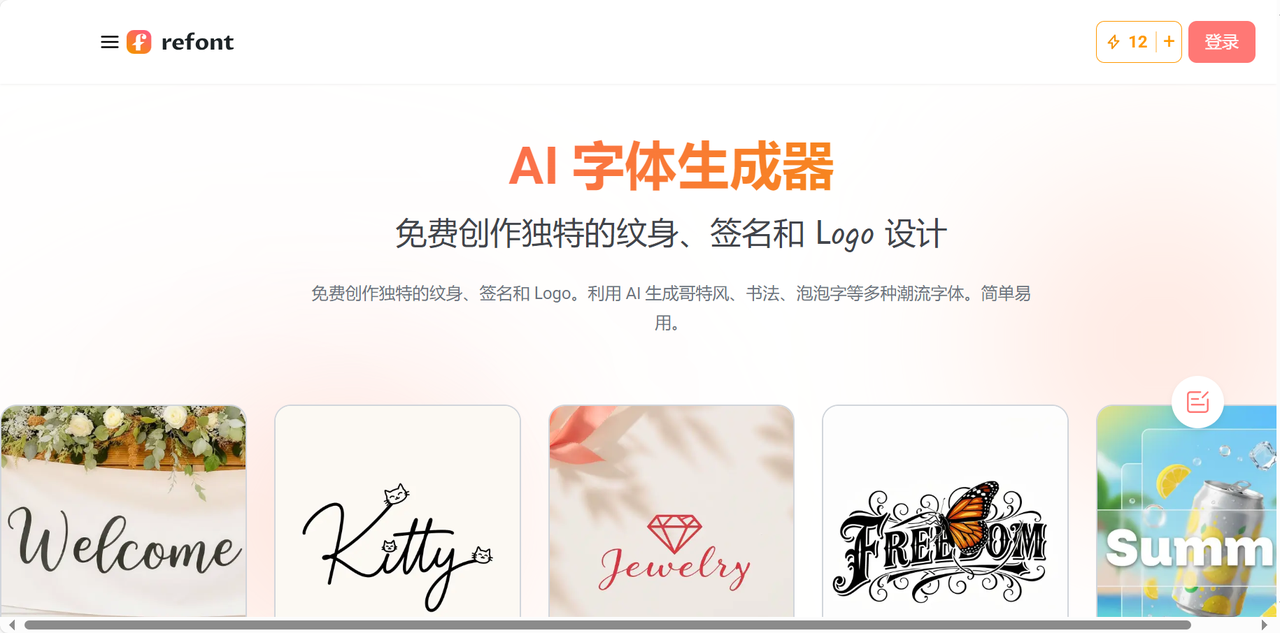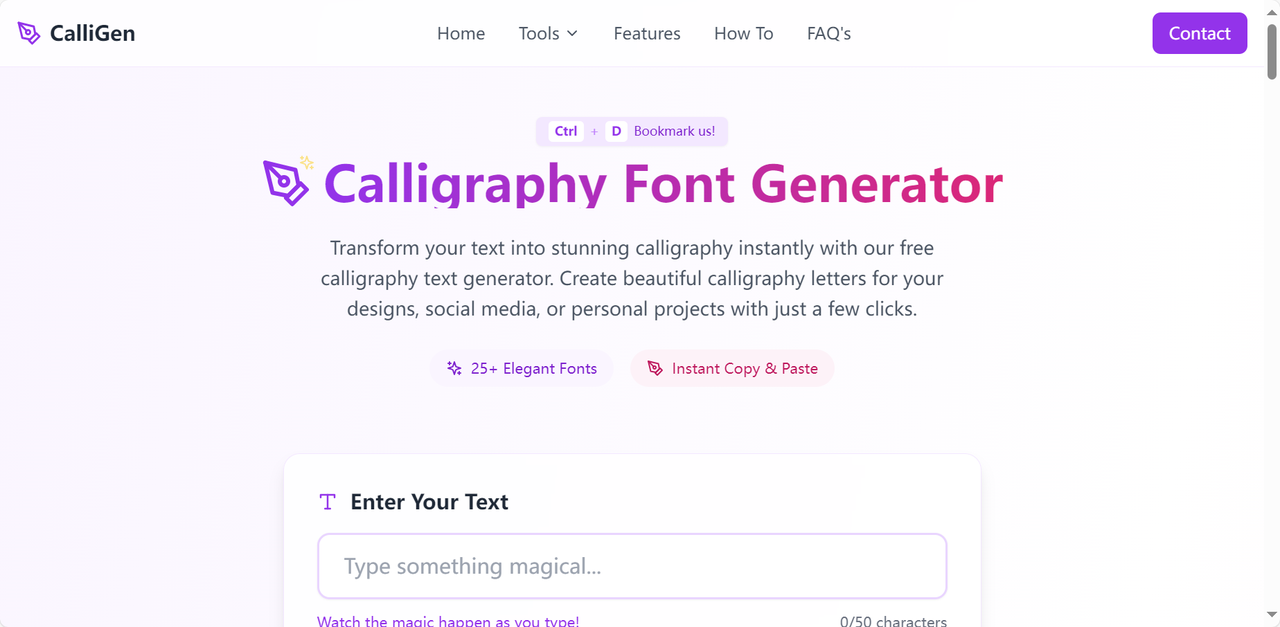
告别手写!在线毛笔字生成工具,透明背景直接下载
没学过书法可以拥有好看的毛笔字字体吗?答案当然是可以!毛笔字不同于日常设计中的其他字体,核心特点在于笔画的粗细变化、飞白墨韵、起收笔锋及手写感,兼具文化意蕴和视觉表现力。而设计作品里经常会用到的毛笔字体正是融合了古代书法的结构特点以及现代数字化设计的简约易读。在线毛笔字生成工具的运行逻辑就是选好字体风格,直接输入你想要的文字,就可以在线获得同款毛笔字,透明背景图片直接下载,拖进任何设计软件里都能用。今天这篇文章,带你认识 4 款实用性极高的在线毛笔字生成工具,一起来看看吧。
一、字由
字由是国内规模领先的字体管理工具,它不仅拥有超多有品质保障的字体资源,还有免费实用的 AI 工具,大大提升你的设计效率。在线生成毛笔字正是需要用到字由的 AI 字体功能,不需要自己写提示词,也不需要懂 AI 模型参数,选择模板、输入文字、一键生成三步搞定毛笔字体。用户只需要在字由官网内找到 AI 字体的页面,可以按照风格进行毛笔字筛选,然后点击“做同款”,就可以一键生成图片同款毛笔字,最好自定义文字的字数和样图内一致,这样生成效果更准确逼真。
我用字由生成毛笔字还是比较频繁的,目前来看它生成的字体结果与默认效果图高度一致,还没有出现过偏差,笔画保留了自然手写感,也不会有文字错位或者变形的问题。而且生成的毛笔字体支持导出透明背景的 PNG 图片,直接拖入 PS 等设计软件即可使用,不用抠图、不用去底,非常方便!
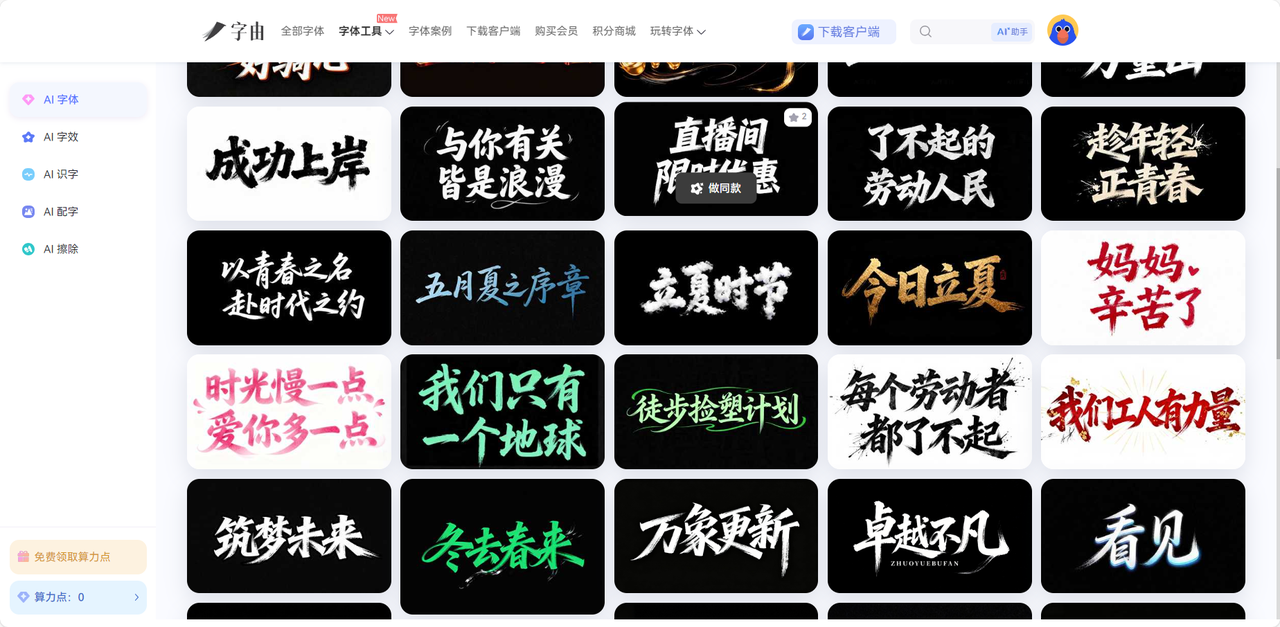
二、Refont AI
Refont AI 是一款以 AI 驱动的书法毛笔字生成工具,支持中文和英文,覆盖草书、隶书、行书等多种字体风格。这款工具最大的亮点是书法风格的 AI 渲染功能,比如选择草书风格,系统会自动模拟草书的笔锋及字形;选择隶书风格则会精准还原“蚕头燕尾”的壁画特征,保证你的字体完全符合书法效果。Refont AI 还内置了名家风格选项,也就是说用它可以模仿一些著名书法家的笔触风格,对于一些书法字体要求高的场景里,这款工具会是设计师的绝佳选择。而且为了还原毛笔字的呈现效果以及真实性,生成字体后可以选择对应的北京,宝库复古纸张、干净白纸、横线作业纸等等,很像是自己在纸上书写文字的视觉效果,满意的话可以直接下载高清图片格式,后续放进其他设计软件也适用。
除此之外,Refont AI 还提供了不同的功能模块,进入该网站后,你可以自由选择 AI 书法生成器、AI 签名生成器、AI 手写生成器、花式字体和书法 Logo 等功能,不需要任何设计基础,只需在输入框中键入或粘贴文字,几秒内即可获得高清、独特的书法字体。
三、Calligraphy Font Generator
如果你想要快速生成英文书法字体,或者你在设计项目中需要一款优雅美观的英文标题字体,但是电脑里又没有安装对应的英文字体库,不妨来试一试 Calligraphy Font Generator。这是一个完全免费的英文毛笔字在线生成平台,拥有几十种书法毛笔字,从古典优雅到潦草奔放,从现代时尚到涂鸦有趣,各种风格应有尽有,大部分字体资源都可以免费商用哦,大家看清楚授权信息即可。用户不需要注册、不需要登录,打开 Calligraphy Font Generator 的官网即可使用,它支持实时预览功能,只需要在输入框内输入文本内容,下方就会实时预览每种书法风格的呈现效果,不满意可以及时更换其他字体风格。
不仅如此,Calligraphy Font Generator 给用户的体验提供了足够的自由度,你可以对生成的毛笔字调整字体大小、行距、字距、颜色等参数,还能选择高分辨率导出,保证字体的清晰度。值得一提的是,该工具的多格式导出功能是很多用户喜爱的,字体文件可以导出为 PNG、SVG、PDF 等多种格式,尤其是 SVG 格式最适合二次编辑,在 Illustrator 或 Inkscape 中打开可以自由调整个别笔画的锚点,设计 logo 或海报时超好用!
四、FontPainter
上面 3 个毛笔字生成工具都是依据字体模板生成对应字体,而 FontPainter 不会被任何现成模板束缚,可以完全靠自己亲手绘制一个毛笔字,满足从零到一的创作需求。FontPainter 是一款实现在线 DIY 字体的编辑生成工具,真正打造一套带有自己笔记风格的专属字体,你想怎么设计就怎么设计。它主要是提供一个在线的 SVG 矢量编辑器,用户只需要进入官网,在对应区域绘制或勾勒每一个字符的笔触,或者选择预设字库里的字形结构,再自己调整节点、曲线、笔画粗细、大小间距等细节。不过这款工具更适合对英文字母进行创作,想要中文毛笔字体的小伙伴可以看看别的工具哈。
最关键的是,在 FontPainter 的网站内,你可以为同一个字母设置多个替代写法,等到下次再生成毛笔字时,系统会随机选择之前设置的不同版本,让最终呈现出来的毛笔字效果更像是自然书写出来的,随性且真实。如果你是一个日常喜欢写点书法,有点毛笔字书写基础的人,也可以显手写一整套字母表再拍照上传到 FontPainter 内,它会自动识别图片内的字体并转换为对应的矢量文字,转换准确率较高,可以还原自己的原生笔迹哦。
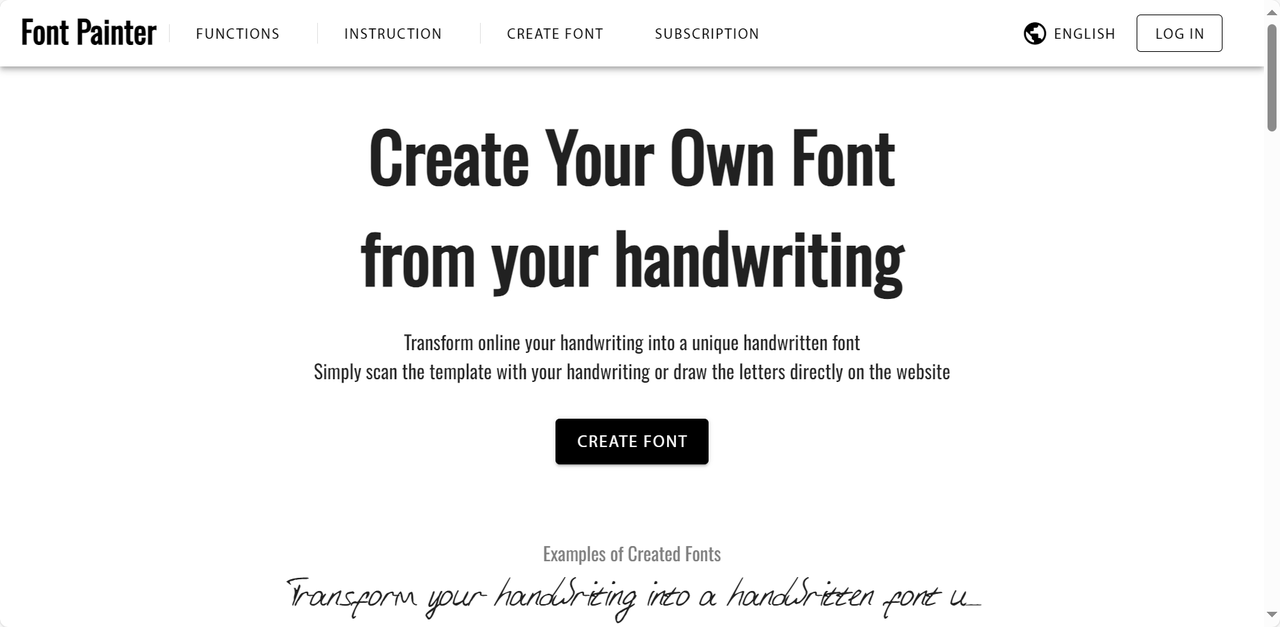
总而言之,毛笔字生成器的出现可以帮助你快速获得想要的毛笔字,哪怕你不懂任何书法技巧,。你只需要打开字由 AI 字体,选个顺眼的模板,输入文案一键生成,好看的毛笔字就到手了!或者你想心血来潮设计一套签名,Refont AI 和 Calligraphy Font Generator 随时待命。如果想要自己创作英文的毛笔字体, FontPainter 是最好的选择。来吧!选择一款毛笔字在线生成工具,亲自去体验一下吧,试过才知道它有多好用。